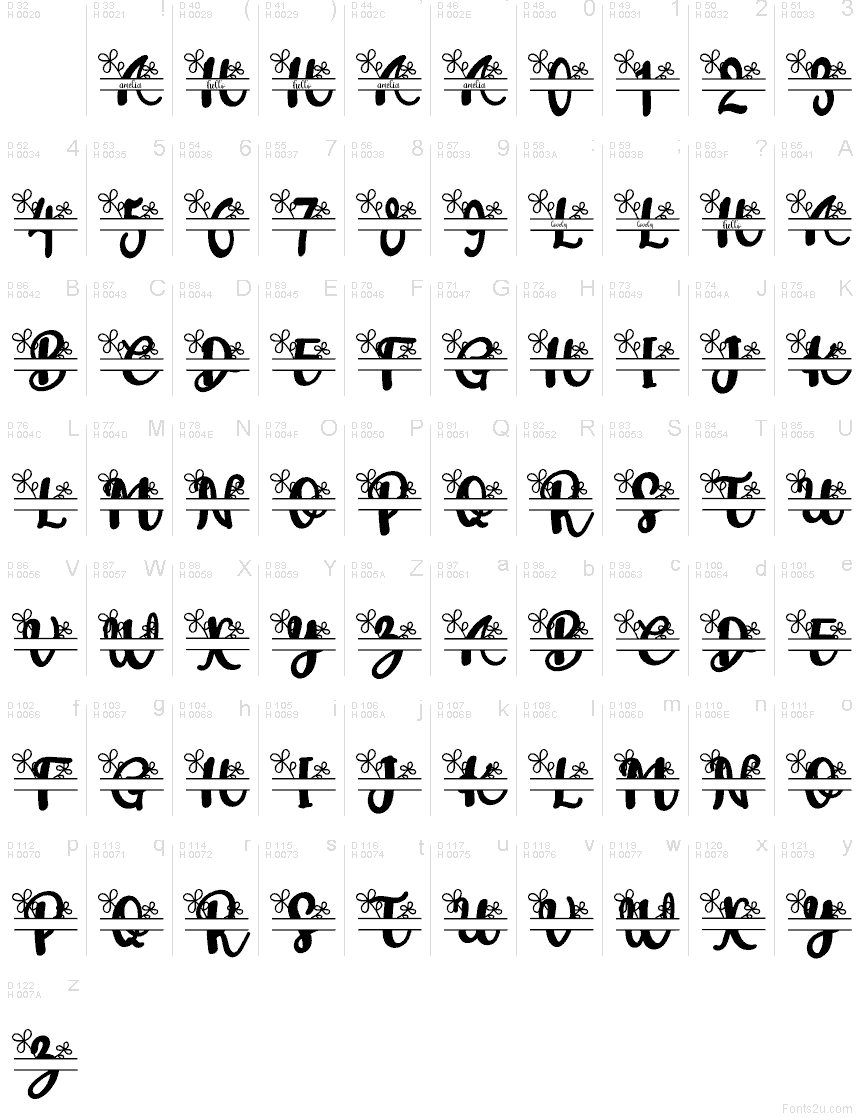
Amelda Monogram - бесплатный декоративный акцидентный шрифт с характерными петлями-монограммами и скругленными буквами с высоким контрастом. Дизайн сочетает в себе крупные инициалы в рукописном стиле с изящными цветочными завитками, придавая каждому знаку оформленный, почти эмблематичный вид.
Amelda Monogram идеально подходит для свадебных приглашений, полиграфии, логотипов, подарочных бирок, брендовой упаковки и монограммных этикеток. Этот бесплатный шрифт отлично справляется с такими задачами: декоративные завитки и центрированные формы букв выглядят как готовый фамильный герб, поэтому даже одна заглавная буква может стать полноценным элементом дизайна.